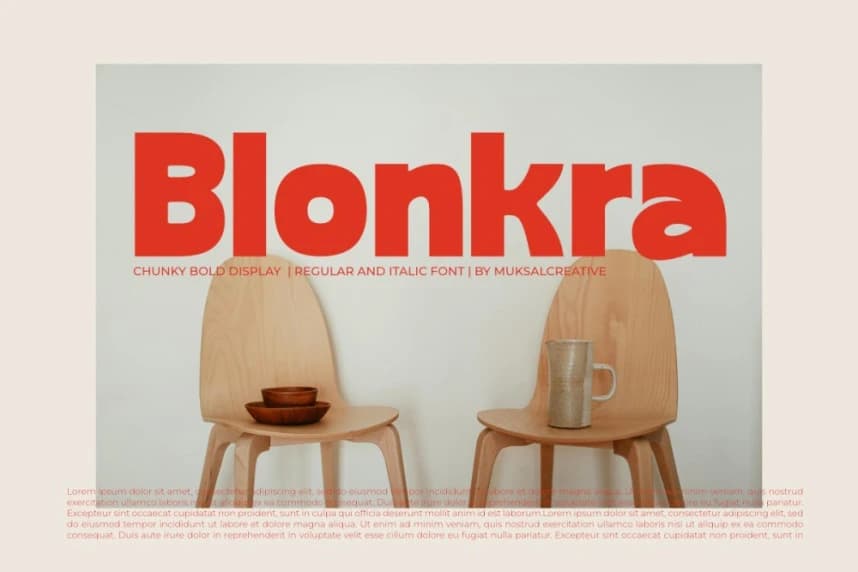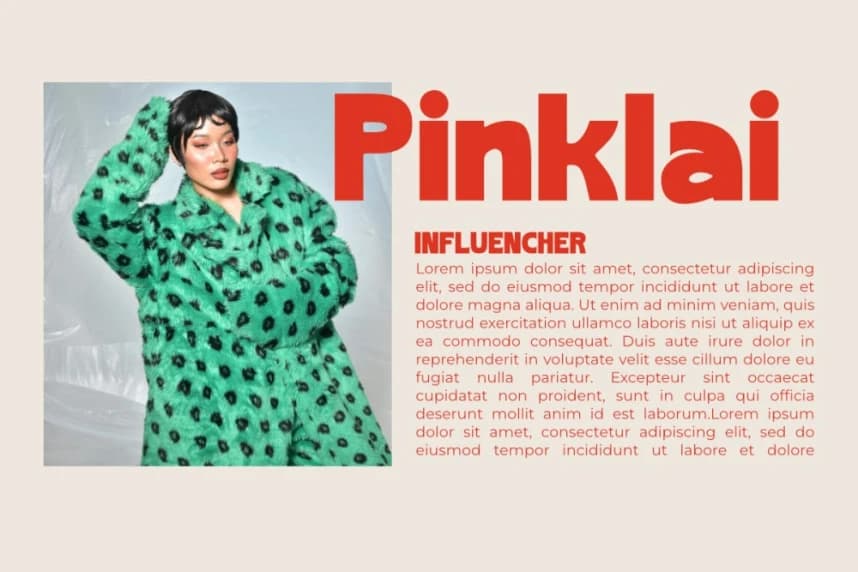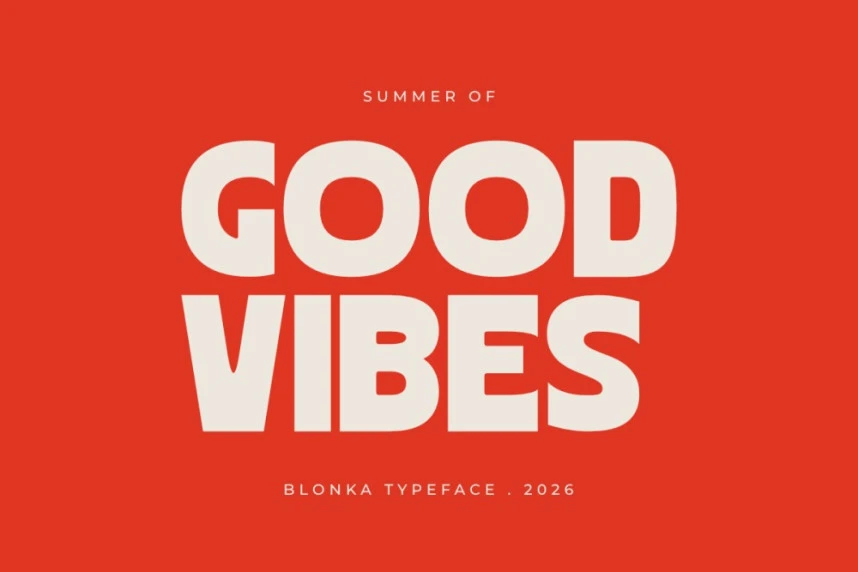
Blonkra Font
Blonkra Font, kalın, gösterişli bir sans-serif türüdür ve kalın, eşit çizgilere sahip, yuvarlak uçlar ile enerjik, organik eğrilerle tasarlanmıştır. Bu yazı tipi sıcak, dinamik ve retro bir görünüm sunar; bu sayede gıda markası tasarımı, afiş tasarımı, logo tipografisi ve dijital başlıklar için idea